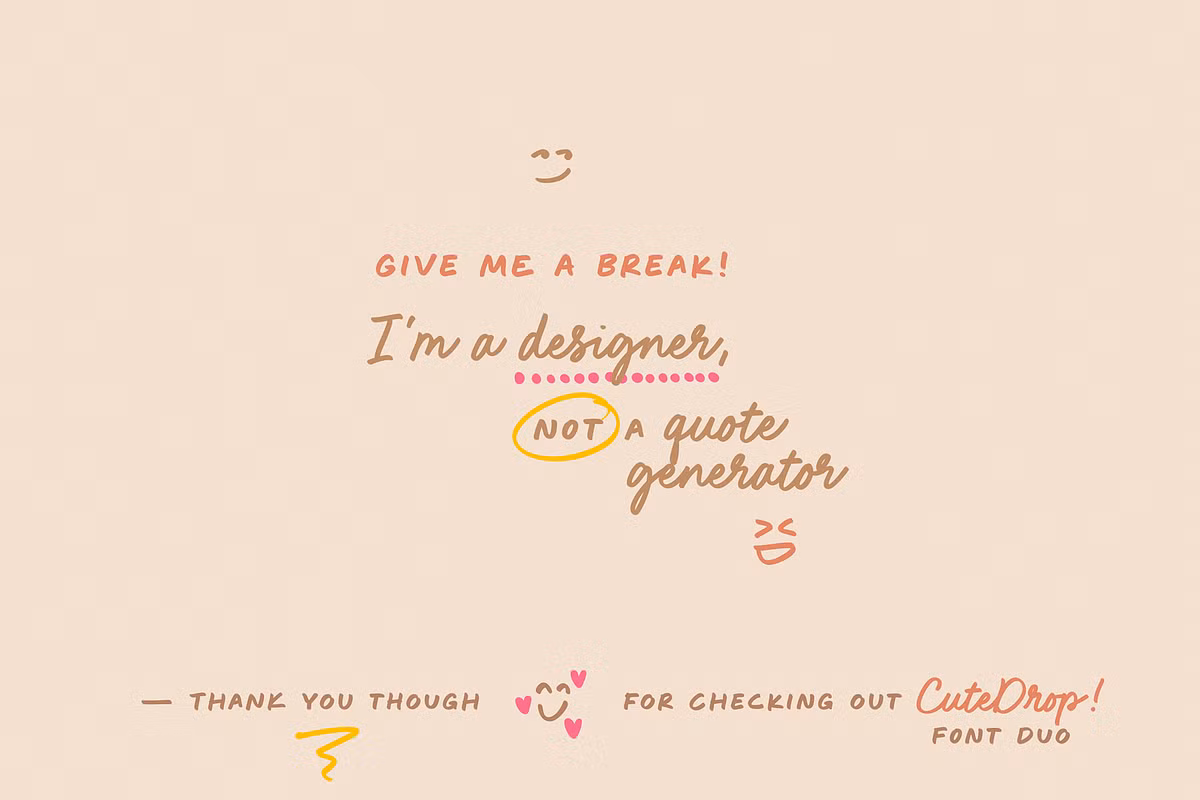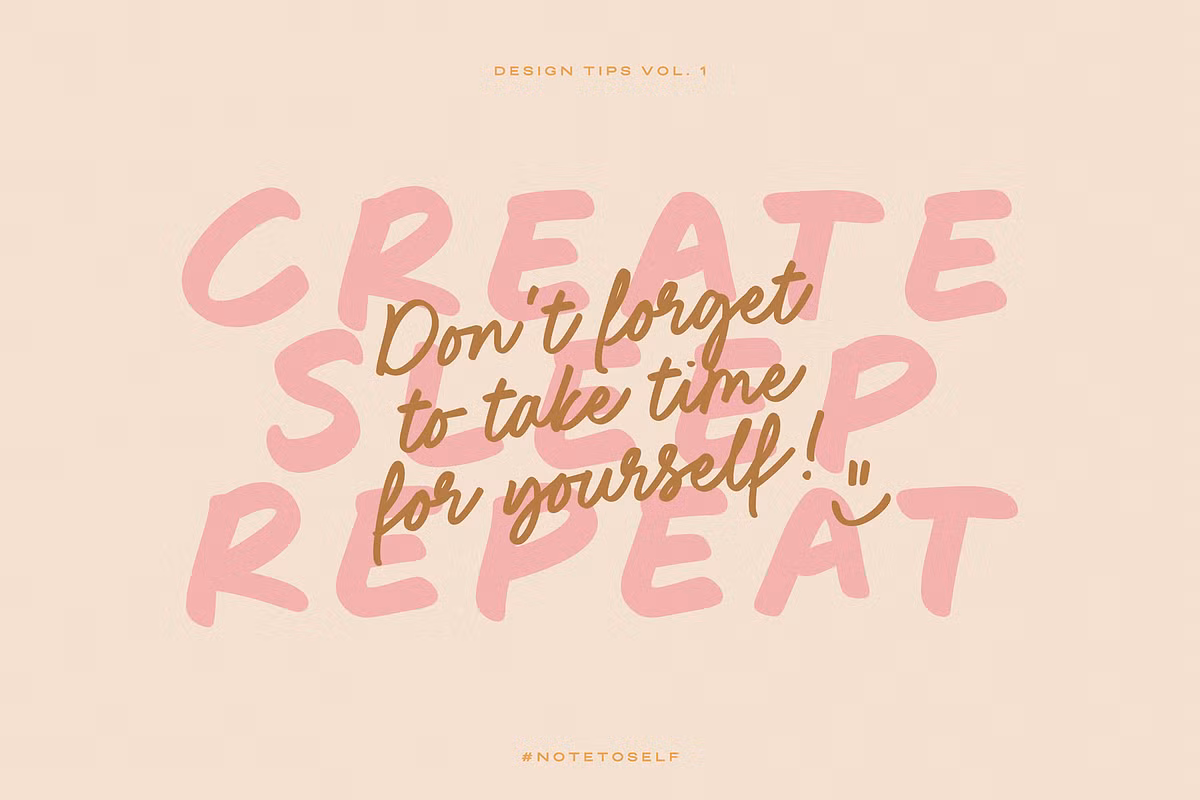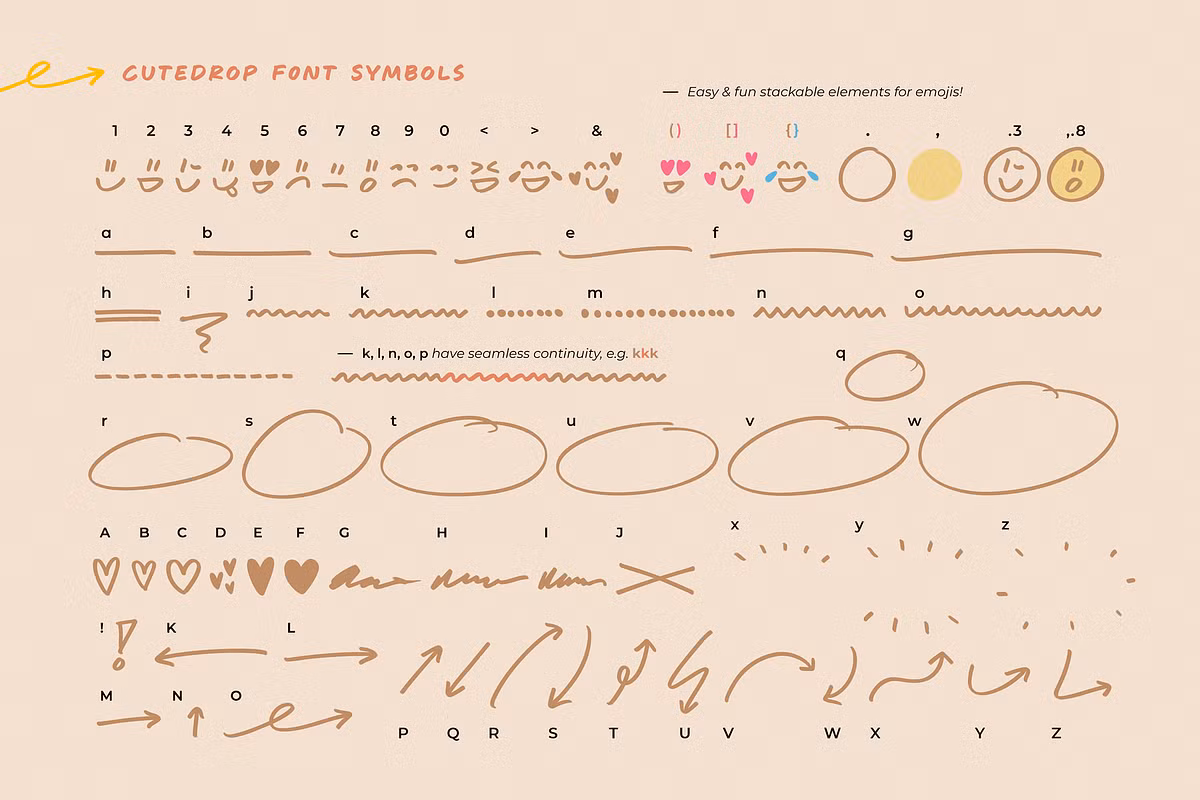
CuteDrop Font Việt hóa là bộ phông chữ thuộc dòng Handwritten Display mang phong cách viết tay siêu đáng yêu, ngọt ngào và tràn đầy năng lượng tươi vui. Với cấu trúc nét chữ phúng phính, các góc bo tròn ngộ nghĩnh và nhịp điệu chữ nhảy múa tự nhiên, phông chữ này mang lại diện mạo vô cùng dễ mến, cực kỳ thích hợp cho các thiết kế bao bì bánh kẹo, nhãn dán trà sữa, sticker quà tặng và các sản phẩm hướng đến giới trẻ hoặc thiếu nhi. Doozypack.vn cung cấp link tải CuteDrop Font viết tay Việt hóa siêu đẹp chuẩn kỹ thuật, giúp bạn sở hữu phông chữ bắt mắt này mà không lo gặp bất kỳ lỗi hiển thị dấu thanh nào khi thiết kế in ấn.
Đặc điểm thẩm mỹ độc đáo của bộ font CuteDrop
CuteDrop không đi theo sự sắc nhọn cứng nhắc của các phông chữ hình học; nó mang đến một ngôn ngữ thị giác đầy tính biểu cảm, vui nhộn và mang lại cảm giác vô cùng thoải mái cho người xem.
Phong cách viết tay ngộ nghĩnh và ngọt ngào như kẹo bông
Đặc trưng lớn nhất của CuteDrop Font Việt hóa là hình khối chữ cái dày dặn, mập mạp và có độ căng phồng đáng yêu. Cấu trúc chữ độc đáo này tạo ra một sức nặng thị giác vượt trội, giúp tiêu đề trên bao bì ngay lập tức chiếm trọn tâm điểm chú ý, khơi gợi sự tò mò và mang lại cảm giác thích thú cho khách hàng.
Nhịp điệu chữ nhảy múa tự nhiên và giàu cảm xúc
Các ký tự của CuteDrop Font viết tay Việt hóa sở hữu đường chân chữ (baseline) nhấp nhô nhẹ nhàng, phá vỡ hoàn toàn sự bằng phẳng đơn điệu của các dòng văn bản máy tính. Phong cách này mang lại cảm giác thủ công tinh tế nhưng vẫn rất sành điệu, cực kỳ ăn ý với các dòng sản phẩm đồ ăn vặt, trà trái cây hoặc các phụ kiện thời trang hướng đến phong cách dễ thương.
Ưu điểm nổi bật của bản CuteDrop Font viết tay Việt hóa siêu đẹp
Khi ứng dụng các phông chữ ngộ nghĩnh vào thị trường trong nước, sự chỉn chu về dấu câu là yếu tố quyết định đến tính chuyên nghiệp của ấn phẩm:
- Khắc phục triệt để lỗi dấu tiếng Việt: Phiên bản Việt hóa đã được đội ngũ thiết kế trau chuốt thủ công từng dấu câu. Các dấu sắc, huyền, hỏi, ngã, nặng được vẽ căng mọng, bo tròn đồng điệu cùng thân chữ gốc, không gây cảm giác chắp vá hay làm biến dạng cấu trúc chữ.